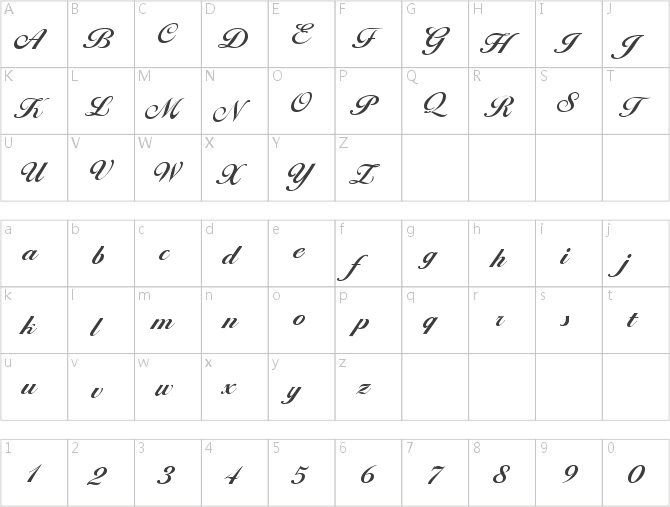
Liffey Script SF 詳情頁
字體名稱: Liffey
Liffey Script SF
Liffey Script SF介紹
Liffey Script SF字體字庫是一款讓人賞心悅目、百看不厭的英文字體,適合各類廣告和產(chǎn)品包裝設計應用,字體大小0.07MB,格式為ttf字體,上傳用戶是rose,作者/版權方為未知